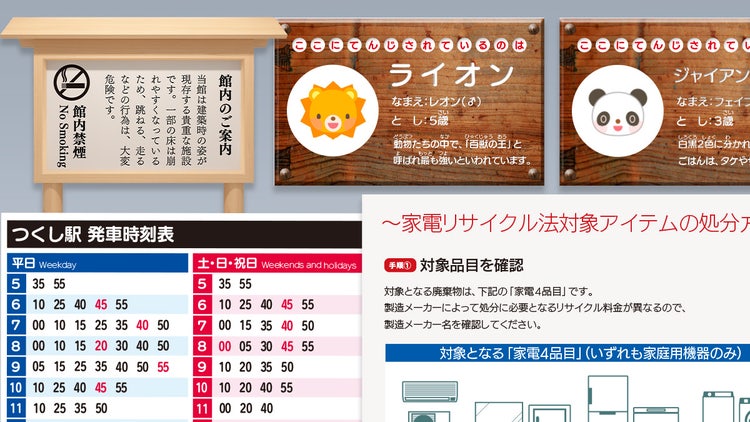
UD書体のきほん|文字とフォントのことはじめ06
Adobe Fonts|UD書体の効果サンプル
見やすく、わかりやすく、読み間違えのない文字を目指して
文字・フォント・デザインの情報をお届けする連載「文字とフォントのことはじめ」、第6回はUD書体について取り上げます。
UD=Universal Designとは、年齢・性別・能力等の違いにかかわらず、誰にとってもわかりやすい、使いやすいデザイン設計のことです。これを書体に当てはめると、どのような人であっても、見やすく、読みやすい文字、読み間違えることのない文字を備えた書体=UD書体ということができるでしょう。
図は2つの書体で「ぽぼ」「835」という文字を表示し、それをぼかしたものです。弱視者の視界を正確に表現したものではなく、あくまで模式的なものですが、それぞれの文字は下の書体=UD書体のほうがはっきりとわかるのではないでしょうか。文字のかたち、ひとつひとつに目を配り、読み間違いのない文字を目指して、現在では、フォントメーカー各社がそれぞれの考えに基づいたUD書体をリリースしています。
この記事では、UD書体の特徴からAdobe Fontsで利用可能なフォントまで紹介していきましょう。
UD書体と一般書体、どこが違うの?
誰にとっても見やすく、読みやすく、間違えることのない文字を目指して作られたUD書体は、一般的な書体とどのような点が異なるのでしょうか。
その方法はフォントメーカーや書体によりさまざまですが、代表的な処理としては「画線の簡略化」「開口部の拡大」「濁点・半濁点の拡大」「読み間違えやすい文字の差別化」があります。
一般的な書体とその書体をUD化した書体を比べた下の図を見ると、「山」はよりシンプルなかたちに、「な」は3画目を離すことでよりはっきりとした文字のかたちに変えていることがわかります。
「C」「3」は開口部を大きくすることで、「C」と「O(オー)」「0(ゼロ)」との読み間違い、「3」と「8」の読み間違いを減らす配慮がされています。
右下の例は、小文字のエル「l」です。こうした文字は前後関係から類推できることも多々ありますが、たとえ一文字で使われたときにも、確実にその文字とわかる、そのような配慮が見て取れます。
Adobe Fonts|UD書体解説
モリサワ・新ゴとUD新ゴの比較例。UD新ゴはAdobe Fontsで利用可能 https://fonts.adobe.com/fonts/a-otf-ud-shin-go-pr6n
「UD書体が誰にとっても見やすく、読みやすいのなら、すべての文字にUD書体を使ったほうがいいの?」
そのような疑問を持つ人もいるのではないでしょうか。
もし、UD書体を使うべきかどうかを迷ったら、いま手がけているデザインは、誰がどのように接するものなのかを考えてみましょう。公共機関のサイン・看板・お知らせのようなものや、警告・注意書き・取扱説明書のようなもの、読み落とさないでほしい文章や読み間違えない配慮が必要なものなら、UD書体を使うほうが文字情報を的確に伝えることができるでしょう。
一方、風合いのある筆文字でお店のイメージを伝えたい、小説やエッセイを流れるように読み進められる仕上がりにしたいというように、ターゲットや目的がはっきりしている場合には、そのニーズに応えられる書体をセレクトするほうが、より効果的なデザインになります。書体はあくまでTPOで選ぶものであり、UD書体はその選択肢のひとつと考えましょう。
Adobe Fonts|UD書体使用例
左:新ゴ/右:UD新ゴ。適切な行間を取り、地色とのコントラストがあれば可読性は十分に担保できる
そもそも、デザインにおける見やすさ・読みやすさ・伝わりやすさは、文字のかたちだけで決定するものではありません。文字の大きさ、配色、レイアウトに気を配らなければ、せっかくのUD書体も力を発揮することはできません。
たとえ、UD書体であっても、目を凝らさないと見えないほど小さく配置されたり、行間がなくタイルのように並べられた文章では読みにくくなってしまいますし(右)、UD書体にカテゴライズされていない書体であっても、十分な視認性・可読性を持つ書体はたくさんあり、使いかたの工夫によって、見間違いや読み間違いを抑える配慮をすることもできるのです(左)。
Adobe Fonts|UD書体使用例
視認性・可読性を求められるシチュエーションではUD書体は非常に効果的です
Adobe Fontsでは、こうしたUD書体を17ファミリー・23書体を利用することができます(2023年8月現在)。
Adobe Fontsで使えるUD書体
UD書体にはその文字のスタイルに応じて、ゴシック系、丸ゴシック系、明朝系等、いくつもの種類があります。ここでは、Adobe Fontsで利用可能なUD書体をカテゴリに分けて紹介します。
*フォント名の後につく( )はAdobe Fontsで利用できるウェイト・スタイル数を示します。
ゴシック系UD書体
Adobe Fonts|UD書体サンプル
ゴシック体は、ユニバーサルデザインと相性のよいスタイルで、現在リリースされているUD書体の多くがゴシックスタイルを採用しています。
何を使うか迷ったら、まずはモリサワ「UD新ゴ」「TBUDゴシック」、フォントワークス「UD角ゴ_ラージ」「UD角ゴ_スモール」をアクティベートしてみましょう。なかでも「UD角ゴ_ラージ」は3ウェイト揃っているので、ランク分けが必要なデザインでもすぐに活用することができます。
丸ゴシック系UD書体
Adobe Fonts|UD書体サンプル
ゴシック体と並んで人気のUD書体が丸ゴシック体です。
ゴシック体よりも親しみを感じやすく、低年齢層にもやさしくアプローチすることができます。Adobe Fontsでは4ファミリーが提供されており、「UD丸ゴ_ラージ」は3つのウェイトを利用できます。
コンデンス系UD書体
Adobe Fonts|UD書体サンプル
商品ラベルや成分表示など、限られたスペースでも読みやすさ、見やすさが必要なときに便利なのが、コンデンス系UD書体です。通常のゴシック系UD書体に比べて幅が狭く設計されており、80なら水平比率80%、60なら水平比率60%というように文字自体にあらかじめ変形がかけられているので、同じスペースでもより多くの文字を表示することができます。
明朝系UD書体
Adobe Fonts|UD書体サンプル
ゴシック・丸ゴシック系に比べると数は多くありませんが、Adobe Fontsでは明朝系UD書体も4書体が利用可能です。通常の明朝体と比べると、線幅の抑揚は抑えられ、よりはっきりとした文字になっています。デザインイメージを考えるうえで、ゴシック・丸ゴシック体よりも明朝体がふさわしいとき、明朝系UD書体は頼もしい選択肢になるでしょう。
UDデジタル教科書体
Adobe Fonts|UD書体サンプル
Adobe Fontsではゴシック体、丸ゴシック体、明朝体以外のUD書体も提供されています。
なかでも注目したいのが、モリサワ「UDデジタル教科書体」です。
手の動きにを重視した文字のかたちが特徴で、ロービジョン(弱視)、ディスクレシア(読み書き障害)にも配慮したデザインになっており、従来の教科書体と比べても、硬筆やサインペンによる手書き文字のような自然な佇まいを備えています。
もともとは教科書での使用を想定して作られた書体ですが、その用途は見やすさ、読みやすさを求めるデザインの現場で急速な広がりを見せています。「UDデジタル教科書体」はいま、UD書体のなかでもっとも注目を集めている書体といっても過言ではありません。